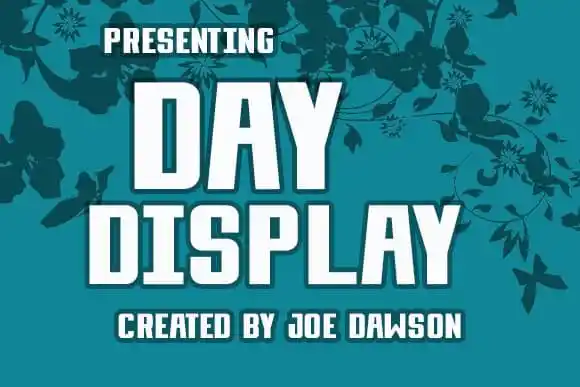
A Day Display Font é uma fonte sans-serif que oferece duas versões diferentes, permitindo escolher as letras mais apropriadas para obter um visual único. Esta fonte é extremamente versátil e se adapta perfeitamente tanto em grandes dimensões quanto em versões menores. Foi criada pelo designer Joe Dawson, conhecido por suas obras incríveis. Day Display é uma tipografia clássica que se destaca pela sua elegância e serenidade, fazendo-a perfeita para aplicações onde a destaque é fundamental, como branding, editoriais, headlines ou embalagens. A proposta de consumo da fonte se estende além do design gráfico tradicional, incentivando designers e criadores a explorarem suas infinitas possibilidades. Engane-se se pensar que Day Display é apenas uma ferramenta para dar vida aos seus projetos visuais; ela pode também ser usada em outras áreas como ilustrações digitais ou até mesmo em design de interface do usuário, tornando-a uma fonte versátil para qualquer aplicação visual.